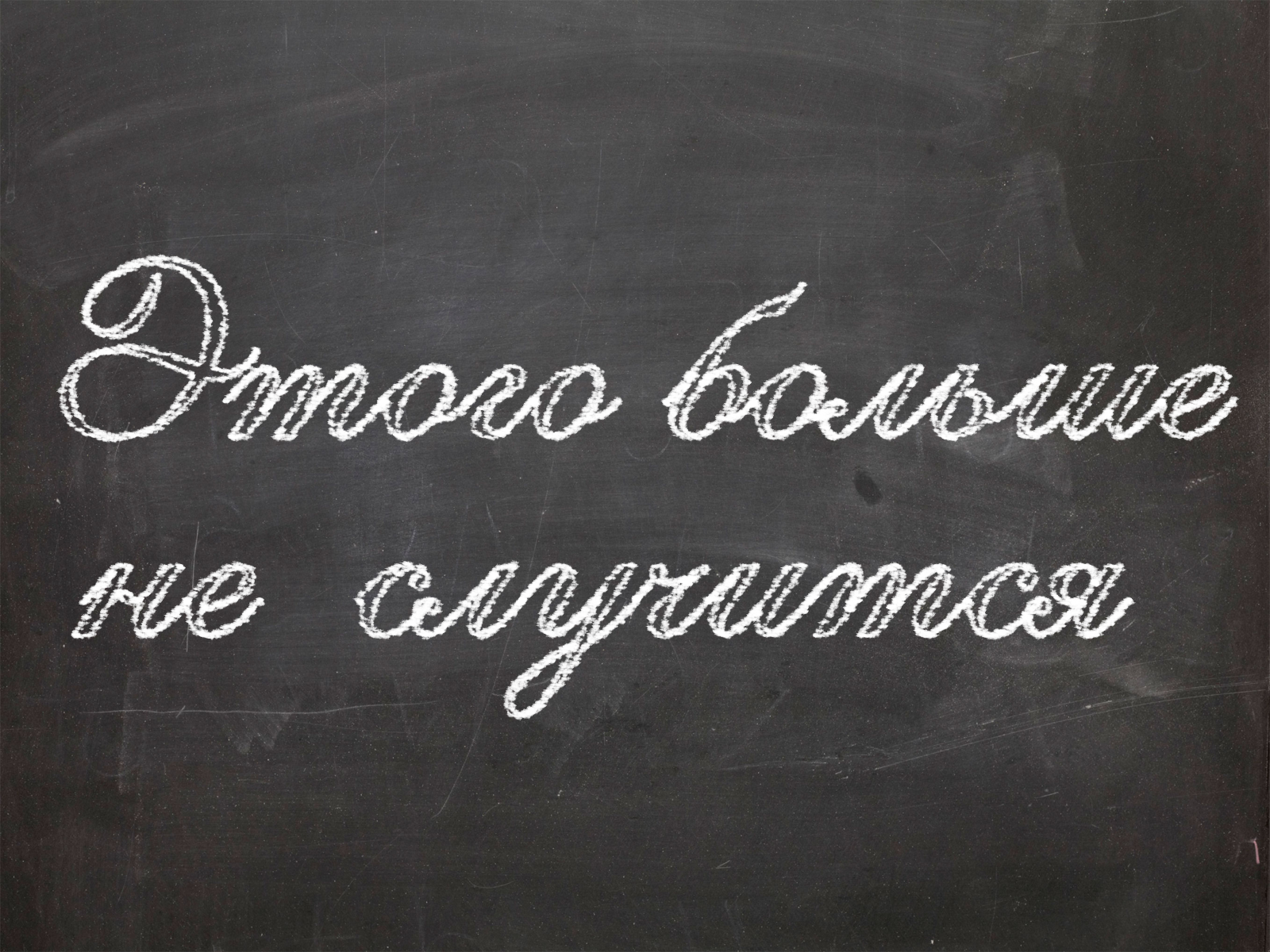
Корпеть над тетрадками, добросовестно выводя завитушки прописных букв, с осени 2016 года финским первоклашкам больше не придется.
Главное внимание на уроках письма будет уделяться работе с компьютерами. Так решили в Финляндии и объявили о предстоящей реформе: в школах страны клавиатура компьютера придет на смену тетрадям и ручкам.
По словам Минны Харманен, которая возглавляет в министерстве образования Финляндии отдел письма, навыки быстрого набора текста на клавиатуре, в отличие от рукописного письма, сегодня играют все более важную роль как в профессиональной деятельности, так и в повседневной жизни. Поэтому ими школьникам предстоит овладевать в полном объеме, а прописным шрифтом, чистописанием — по желанию. Впредь если дети и будут писать от руки, то исключительно печатными буквами.
Печатная скоропись?
Сама по себе идея не нова: в начальных школах некоторых федеральных земель Германии уже используют исключительно печатный шрифт. Да и в других, как правило, стал привычным так называемый «письменный упрощенный шрифт». Здесь буквы тоже напоминают печатные, соединяющиеся между собой соответствующими закорючками.
Разработал этот шрифт Немецкий союз начальных школ (Grundschulverband) в ответ на жалобы педагогов и родителей по поводу «сложностей чистописания» еще в 1980-е годы.
Почерк — индивидуален!
Характерно, что в масштабах целой страны от рукописной прописи первой отказывается именно Финляндия, школьники которой лидируют по результатам международного исследования PISA и которая считается одной из самых передовых стран мира в области образования. Косвенно проблемы, связанные с чистописанием, подтверждают и результаты эксперимента, проведенного с первоклассниками в Канаде. Одну группу ребят обучали прописному шрифту, другую — печатному, третью — сначала печатному, затем прописному. «Дети, которым пришлось учить и печатный, и письменный шрифт, ощутимо отстали от своих сверстников «, — рассказывает Гидо Ноттбуш (Guido Nottbusch), профессор кафедры педагогики начального образования университета Потсдама. Что понятно: им пришлось усваивать два шрифта.
Писать — значит думать
Навык рукописного письма необходимо сохранить хотя бы как элемент культуры, — с этим соглашаются все специалисты.
Профессор кафедры педагогики университета Регенсбурга Ангела Эндерс (Angela Enders) подчеркивает, что упразднение прописи повлечет за собой изменение мыслительной деятельности школьников. По ее словам, тексты, написанные от руки, нужно лучше продумывать, чем те, которые набираются на клавиатуре компьютера. «Электронный текст» незачем продумывать заранее, ведь все можно изменить, переставить местами, да и правописание проверит тоже компьютер. Работая над рукописным вариантом, дети скорее научатся мыслить логично, последовательно и целенаправленно, поясняет профессор Эндерс.
Кроме того, процесс «выписывания» букв необходим для развития мелкой моторики у детей, — в один голос уверяют ученые и педагоги. Писать ручкой означает с одной стороны — записывать определенную информацию. А с другой — это когнитивный и координационный процесс, далеко выходящий за рамки обыкновенной «фиксации информации», настаивает Кристиан Марквардт (Christian Marquardt) научный советник Института письменной моторики (Schreibmotorik Institut) в баварском Херольдсберге (Heroldsberg).